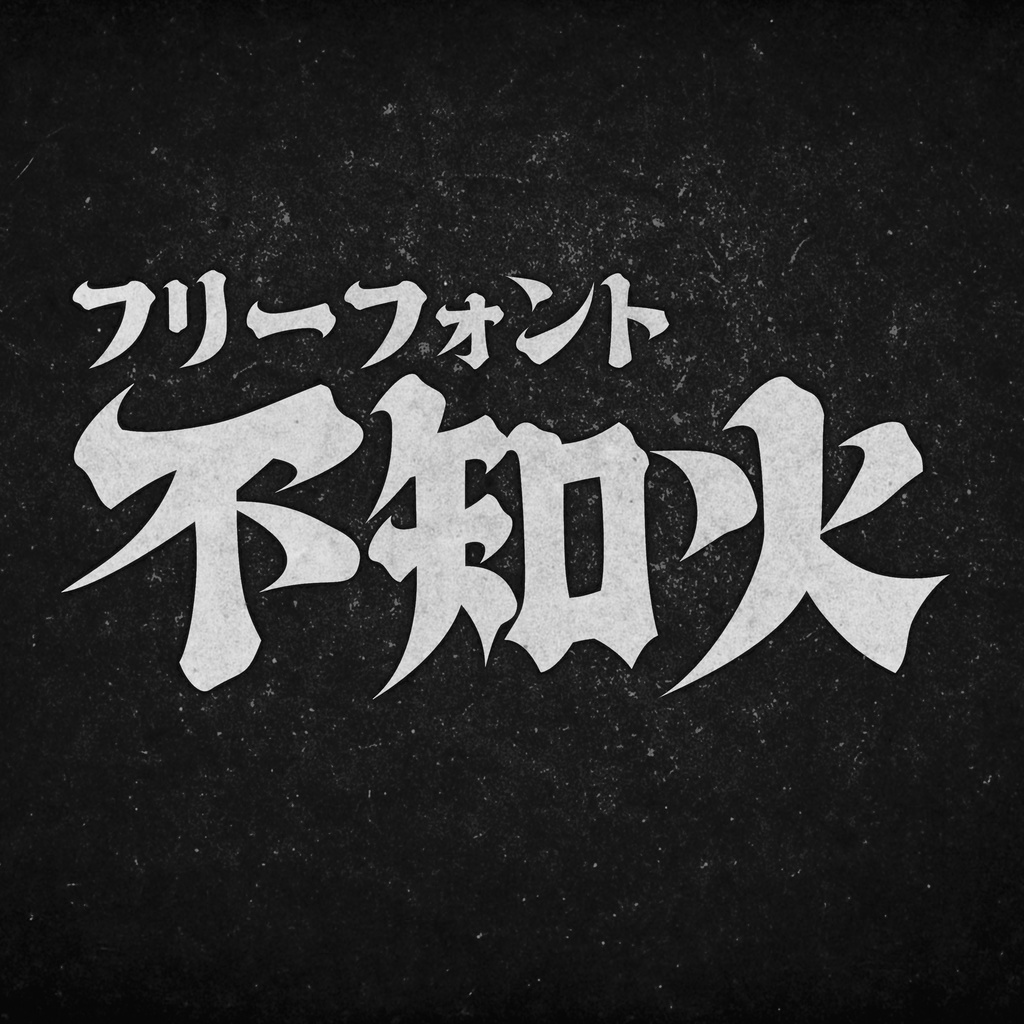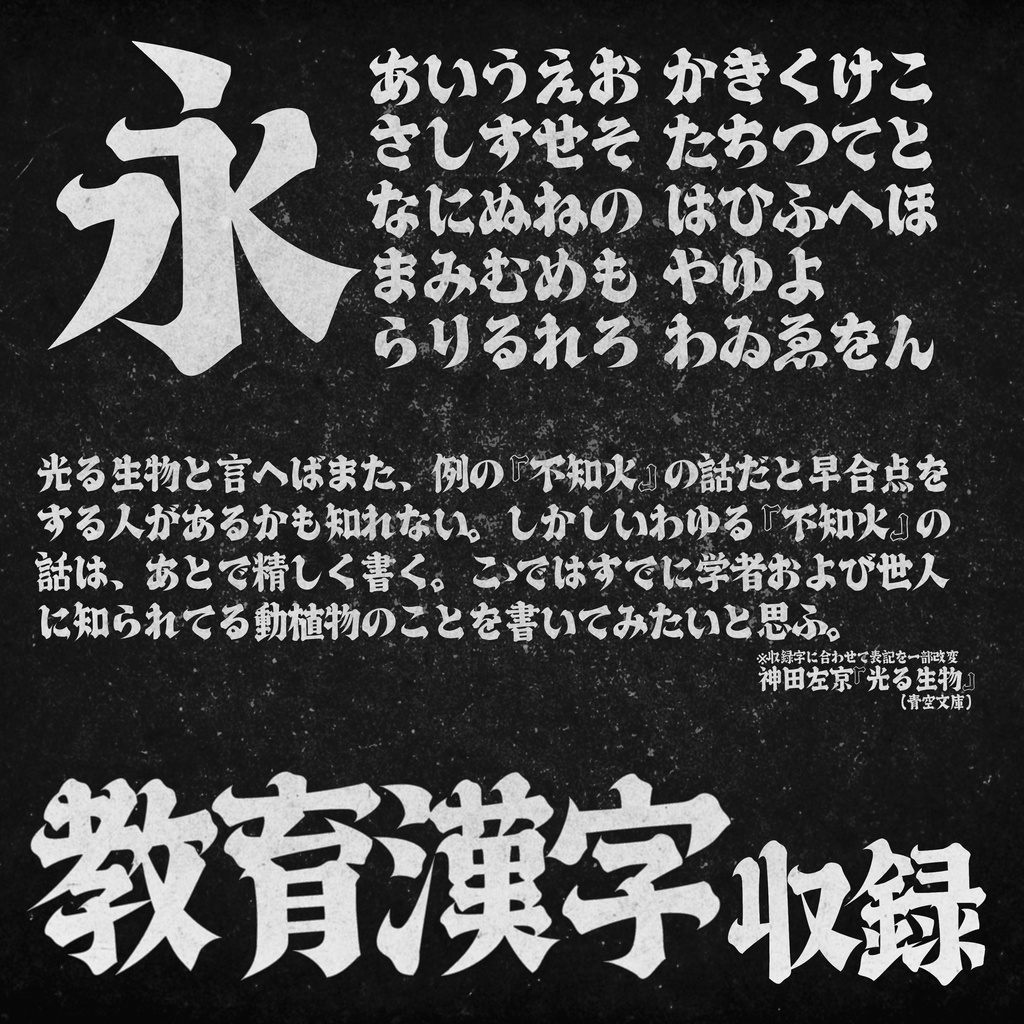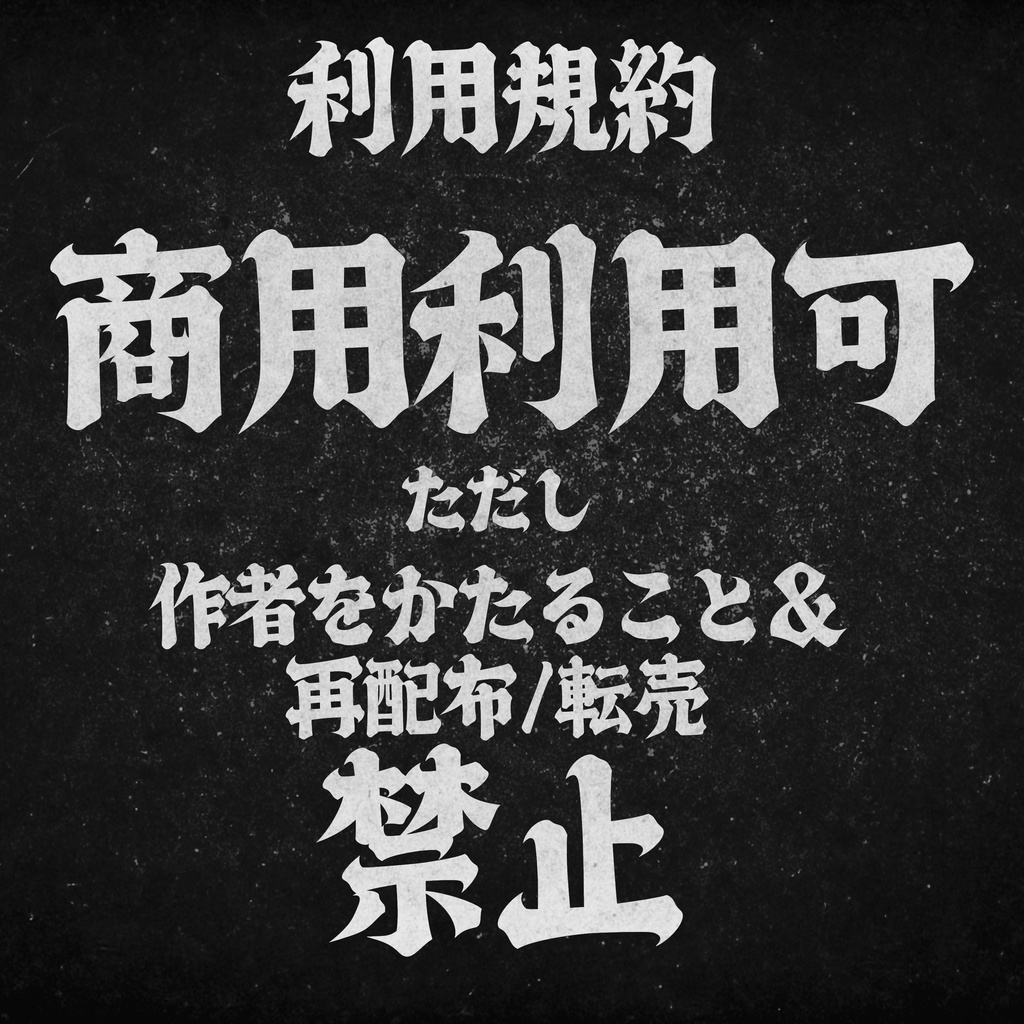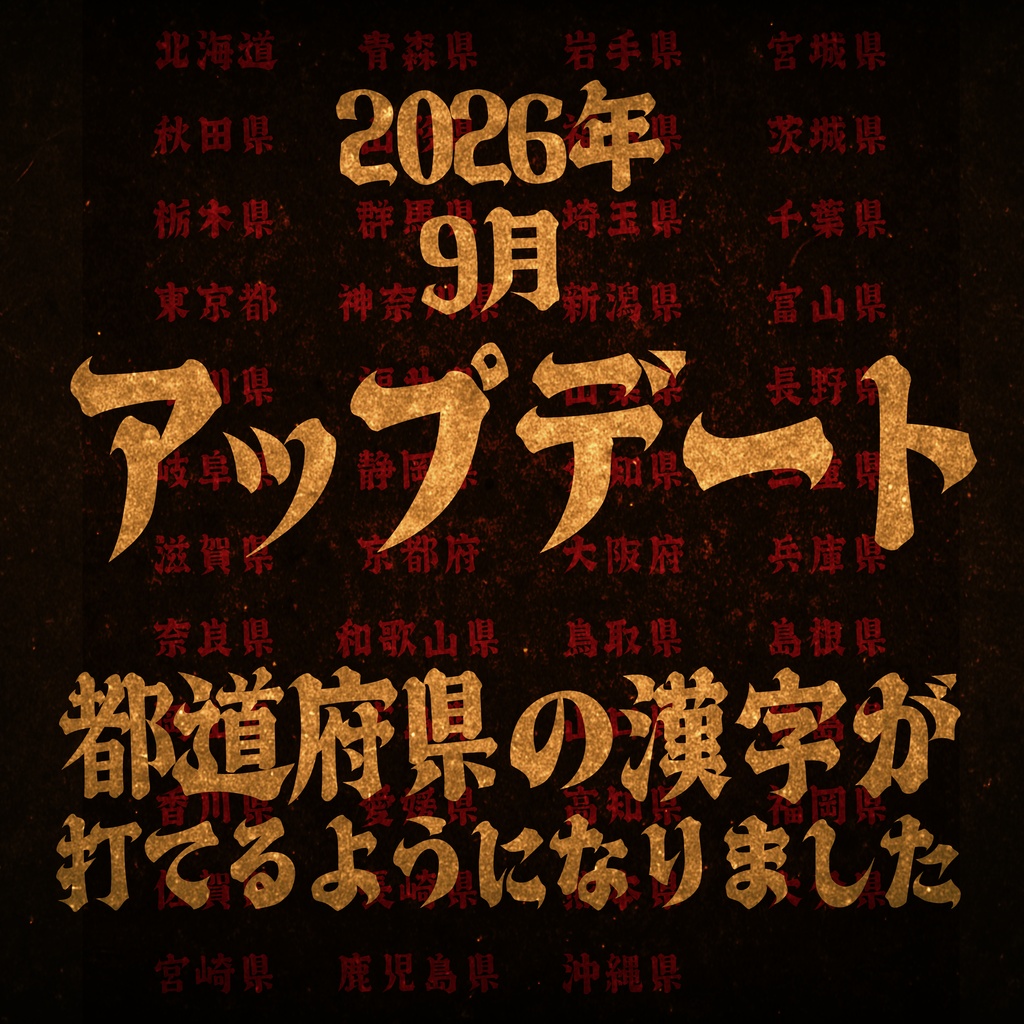
【フリーフォント】不知火(しらぬい)
【このフォントについて】 視認性と力強さの両立を目指した筆文字風デザイン書体です。 無償利用・商用利用問わず、自由にご使用いただけます。 印刷物のみならず、ゲームやWebなど何にでもご活用ください。 ただし、「作者を騙ること」「再配布/転売」は禁止とします。 当フォントを利用した制作物などを、X(旧Twitter)で報告していただけると、とても励みになります。 不具合の修正や新しいグリフの追加が行われる可能性がありますので、最新のバージョンをご確認ください。 【すずみばと書林】 《もじピジョン》と《Suzumi Designs》による2人組のフォント制作ユニットです。 共同制作のフォントを配布・販売しています。 「書林」は本来「多くの書籍が集まるところ」という意味ですが、ここでは「多くの書体が集まるところ」という意味を込めて名付けました。 新作フォントの公開やバージョンの更新情報はそれぞれのX(旧Twitter)でアナウンスしています。当フォントダウンロードの折には、フォローしていただけると幸いです。 《すずみばと書林/BOOTH》https://suzumi-bato.booth.pm/ 《もじピジョン/X(旧Twitter)》https://twitter.com/Moji_Pigeon 《Suzumi Designs/X(旧Twitter)》https://twitter.com/Suzumi_Designs +++++++++++++++++++++++++++++++++++++++++ 【収録文字】 ひらがな・カタカナ・英数字・一部約物・漢字(教育漢字)+ 「廷」(※元々「延」と間違えて登録していた分) (最新ver.2.0) 【更新履歴】 ver.1.0 リリース ver.1.1 誤字の修正「達」「延」「疑」「裏」「革」「救」「身」「射」「配」「様」+ 「廷」を追加 ver.1.2 不具合を修正しました(システム面の修正で、内容に変更はありません)。 ver.1.3 Office使用時の問題を修正しました(システム面の修正で、内容に変更はありません)。 ver.1.4 縦書きに対応しました。 ver.1.5 「〜」の表示安定化/縦書き時の形状訂正の他、縦書き時1バイト文字の回転用グリフを追加しました。 ver.1.6 縦書きグリフを追加しました。 ver.1.7 「党」と打つと「堂」が表示される問題を修正しました。 ver.2.0 2017年改定後の教育漢字(都道府県の漢字)を追加しました。 【利用規約】 ・利用条件 1)当フォントを入手・使用したことによるいかなる損害も使用者自身が責任を負うものとします。 2)無償利用・商用利用ともにご自由にお使いいただけます。 3)クレジットの表記は不要です。 4)当フォントを加工・変形してご利用いただけます。 5)ゲームやWebサイトに埋め込んでご利用いただけます。 ・禁止事項 1)当フォントを公序良俗に反する目的で使用することはできません。 2)当フォントを利用したロゴマーク等の商標登録はできません。 3)当フォントデータ・プログラムを、無断で改変したものを配布・販売することはできません。 4)当フォントの制作者を騙った発言等はできません。 その他、お問い合わせは以下のメールアドレスにお願いします。 suzumi.bato@gmail.com